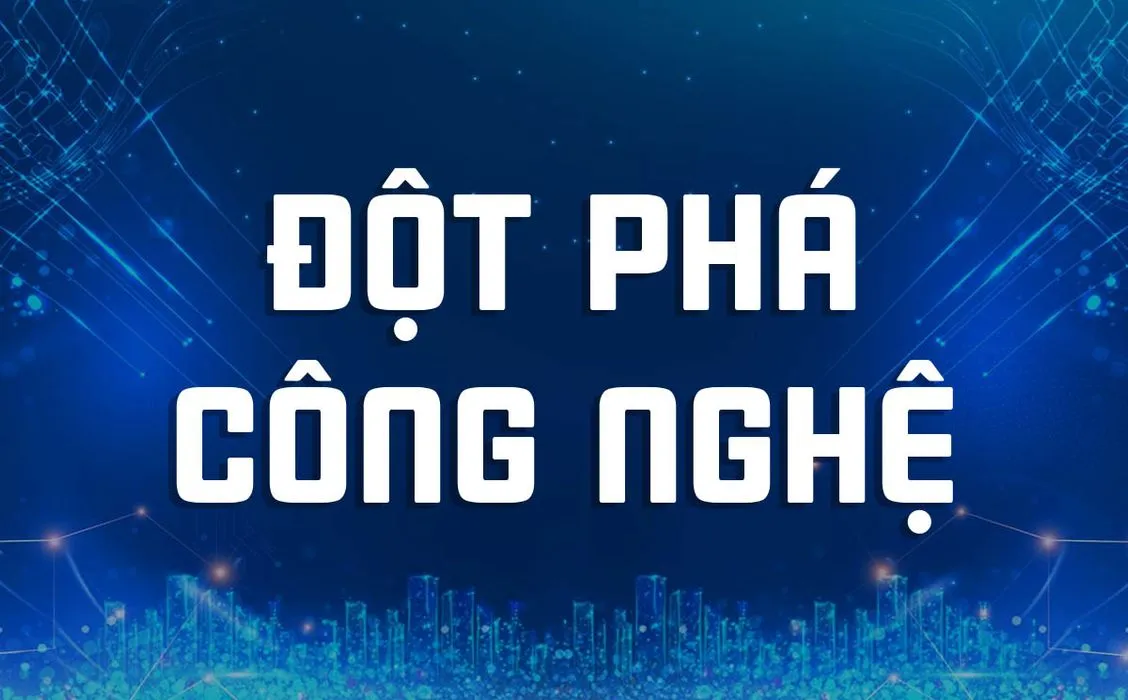
Font chữ hiện đại cứng cáp cho lĩnh vực thể thao điện tử SVN Cintra miễn phí
Trong thế giới thiết kế đồ họa thể thao điện tử (Esports) ngày nay, việc lựa chọn một bộ phông chữ phản ánh được tinh thần mạnh mẽ, tốc độ và tính cạnh tranh là yếu tố then chốt tạo nên dấu ấn thương hiệu. Font chữ SVN Cintra ra đời như một giải pháp hoàn hảo với đường nét góc cạnh, hiện đại và vô cùng cứng cáp, mang đến luồng gió mới cho các nhà thiết kế đồ họa game. Được Việt hóa chuẩn xác và cung cấp hoàn toàn miễn phí, SVN Cintra hứa hẹn sẽ nâng tầm mọi sản phẩm truyền thông của bạn từ logo, banner giải đấu cho đến giao diện stream chuyên nghiệp.
Font Chữ Hiện Đại Cứng Cáp Cho Lĩnh Vực Thể Thao Điện Tử SVN Cintra Miễn Phí – Giải Pháp Thiết Kế Đột Phá
Ngành công nghiệp thể thao điện tử luôn đòi hỏi sự đổi mới không ngừng trong phong cách thị giác. Một banner quảng bá giải đấu hay một logo đội tuyển không thể sử dụng những phông chữ mềm mại, uốn lướt thông thường. Thay vào đó, thiết kế Esports cần sự chắc chắn, uy lực, mang hơi hướng tương lai và bứt phá giới hạn. Font chữ hiện đại cứng cáp cho lĩnh vực thể thao điện tử SVN Cintra được sáng tạo ra nhằm đáp ứng chính xác những tiêu chuẩn khắt khe đó.
Với hình khối hình học chuẩn mực, các đường cắt cúp sắc sảo cùng tỷ lệ khung chữ tối ưu, SVN Cintra tạo ra cảm giác sống động, bùng nổ năng lượng ngay từ cái nhìn đầu tiên. Phiên bản Việt hóa của font chữ này đã khắc phục hoàn toàn lỗi vỡ nét hoặc lệch dấu Tiếng Việt – một vấn đề vô cùng phổ biến khi các designer Việt Nam sử dụng các phông chữ gaming quốc tế. Dù bạn đang thiết kế áo đấu, làm thumbnail YouTube hay dựng khung hình livestream, SVN Cintra đều đem lại sự nhất quán và chuyên nghiệp vượt trội.
1. Thiết Kế Góc Cạnh, Hình Khối Hình Học Đậm Chất Future & Gaming
SVN Cintra gây ấn tượng mạnh mẽ nhờ vào ngôn ngữ thiết kế hình khối (geometric typography) kết hợp với các đường vát góc đầy tinh tế. Mỗi ký tự đều được tính toán tỷ lệ tỉ mỉ để tạo ra độ dày dặn, cứng cáp nhưng không hề thô kệch. Phong cách mang hơi hướng tương lai (futuristic) giúp phông chữ này cực kỳ phù hợp với các bộ môn thể thao điện tử đình đám như bắn súng (FPS), đối kháng (MOBA) hay đua xe (Racing).
• Đường nét mạnh mẽ: Thể hiện sự kiên cường, tinh thần chiến đấu và bản lĩnh của các game thủ.
• Độ nảy thị giác cao: Các nét cắt độc đáo giúp từ khóa chính trên banner dễ dàng thu hút ánh nhìn của khán giả.
• Sự cân bằng hoàn hảo: Giữ được độ đọc tốt (legibility) ngay cả khi áp dụng các hiệu ứng đồ họa phức tạp như 3D, Gradient hay Neon Glow.
2. Việt Hóa Hoàn Chỉnh, Tương Thích Mượt Mà Với Tiếng Việt
Một trong những điểm cộng lớn nhất của phiên bản SVN Cintra chính là quá trình Việt hóa tỉ mỉ. Các dấu thanh (sắc, huyền, hỏi, ngã, nặng) cũng như các ký tự đặc trưng của tiếng Việt (ê, ô, ơ, ư, đ…) được thiết kế riêng biệt để đồng bộ hoàn toàn với cấu trúc cứng cáp của bộ font gốc. Bạn sẽ không còn gặp phải tình trạng dấu bị lệch vị trí, quá nhỏ hoặc làm mất đi tính thẩm mỹ chung của tác phẩm thiết kế.
• Giữ nguyên tinh thần thiết kế: Dấu tiếng Việt được cách điệu góc cạnh, hòa quyện tự nhiên với tổng thể ký tự mà không gây rối mắt.
• Tối ưu hóa quy trình làm việc: Designer tiết kiệm tối đa thời gian hiệu chỉnh thủ công từng ký tự khi gõ nội dung tiếng Việt.
3. Tính Ứng Dụng Đa Năng Trong Nhiều Sản Phẩm Đồ Họa Esports
SVN Cintra không chỉ giới hạn trong một dạng bài viết hay một loại hình thiết kế nhất định. Nhờ tính linh hoạt cao, bộ font này đã trở thành sự lựa chọn hàng đầu của rất nhiều Creator, Designer và các đơn vị tổ chức giải đấu thể thao điện tử tại Việt Nam.
1. Thiết kế Logo & Brand Identity: Tạo dựng bản sắc riêng biệt, ngầu và đầy cá tính cho các clan, guild hoặc đội tuyển Esports chuyên nghiệp.
2. Banner & Poster Giải Đấu: Làm nổi bật tiêu đề giải đấu, tiền thưởng và lịch thi đấu với độ hiển thị ấn tượng.
3. Overlay Stream & Thumbnail Content: Giúp các streamer thu hút lượt click trên YouTube, Facebook Gaming hay Twitch nhờ tiêu đề sắc nét, thu hút.
4. In Ấn Merchandising: Phù hợp để in ấn lên áo đồng phục thi đấu, nón, áo hoodie và các phụ kiện gaming gear.
4. Tối Ưu Hiển Thị Rõ Nét Trên Mọi Thiết Bị Và Độ Phân Giải
Sở hữu khoảng cách giữa các chữ cái (kerning) được căn chỉnh chuẩn xác, SVN Cintra đảm bảo khả năng hiển thị tuyệt vời trên mọi loại màn hình. Dù được sử dụng trên màn hình di động nhỏ gọn hay các màn hình LED khổng lồ tại các sân vận động thi đấu Esports, phông chữ vẫn giữ nguyên độ sắc nét, không bị nhòe hay vỡ nét.
Đặc biệt, khi kết hợp SVN Cintra với các công cụ đồ họa hàng đầu như Adobe Photoshop, Adobe Illustrator hay Premiere Pro, font chữ này hoạt động cực kỳ mượt mà. Bạn có thể dễ dàng biến tấu với các hiệu ứng biến dạng (warp), ép kim (metallic), tạo khối 3D hoặc lồng ghép hình ảnh vào bên trong chữ để tạo ra những sản phẩm đỉnh cao.